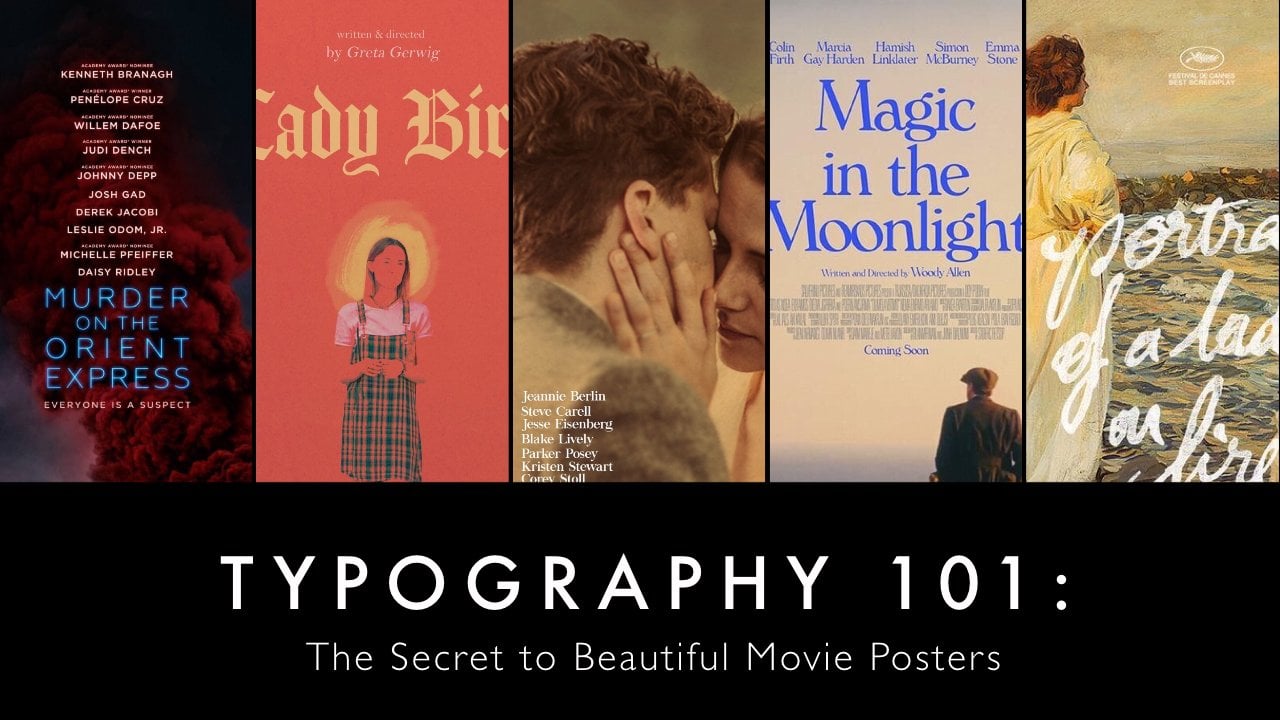
Tipografía 101: el secreto para hermosos carteles
¿Alguna vez te has visto fascinado por un póster de películas absolutamente hermoso? ¿Y te preguntas por qué es tan hermoso? Bueno, has venido al lugar correcto.
En última instancia, el secreto de los hermosos pósters de películas es la tipografía, el arte de usar texto. En este curso de tipografía 101, aprenderás qué hace que ese póster de películas sea tan hermoso y aprenderás cómo diseñar un póster de películas como ese.
1. Tipografía 101: tráiler de introducción: ¿ Alguna vez te has encontrado siendo hipnotizado por un póster de película absolutamente hermoso? Y te preguntas, ¿por qué es esto tan hermoso? ¿ Es la fuente que utilizan para un espaciado perfecto entre las letras son disposición proporcional de los textos o vía combinación de colores estáticos. En última instancia, para carteles de película secretos a bellos es la topografía. El arte de usar texto. En este curso tipo de grafeno 0101, aprenderás qué hace tan lamentable ese póster de película. Y aprenderás a diseñar un hermoso póster de película así. Epigrafía uno a uno, ya que no se requiere un software costoso de conocimientos básicos sobre diseño gráfico o donde estés principiante al diseño gráfico o simplemente tienes curiosidad, este curso es para ti. Entonces, ¿estás listo para desbloquear el secreto? 2. Typeface vs. Font y qué fuente debe usar en un diseño: Hola a todos. Bienvenido al tipo de grafeno 0101 es secreto a hermosos carteles de película. En esta lección, aprenderemos cuál es la diferencia entre tipografía y fuente para el diseño. En primer lugar, tipografía versus engendrado. Una tipografía incluía múltiples fuentes de la misma familia, mientras que una fuente con un peso y un tipo de tamaño específicos dentro de esa familia. Por ejemplo, y este cartel, la tipografía es Futura. Pero más específicamente, la fuente es 22 largometraje en medio para los nombres de las actriz y 72 futuro o extra negrita para el título. Ahora, elegimos unas preguntas para cada diseñador ¿qué fuente usar en tu diseño? Hay dos factores a considerar a la hora de elegir una fuente. Practicidad y estética. Practicidad significa legibilidad. No importa lo bonito que sea cartelar, si la fuente es elegible, fan, es un mal diseño. Entonces, ¿cómo sabes si la fuente es práctica o no? Hágase esta pregunta, ¿ es esto fácil de leer? Preste atención al espaciado entre letras y espaciado entre palabras. Preste atención a la conducción de una brecha entre las líneas. Preste atención al color. Y si no hay suficiente contraste entre el color del texto y el fondo, será difícil de leer. Y por último, como regla general de oro, unas fuentes cursivas y caligráficas, más difíciles de leer y fuentes simples y mínimas. A continuación, hablemos de un set X. Un póster de película es hermoso o no porque la fuente en sí es hermosa. Pero donde sea porque la fuente simplemente va muy bien. El tema de la película. Por ejemplo, cuando vayas a Pinterest y busques una tipografía hermosa, se mostrarán muchas fuentes como esta. Echemos un vistazo más de cerca a esta tipografía. Fuente es Lovelace, fuentes zeta gris claro extra. El diseño del cisne es bastante increíble. Está compuesta por trazos gruesos y delgados. Esos detalles le dan a esta fuente una sensación muy elegante y elegante. No obstante, no tendría sentido que pongas una fuente como esta en carteles en movimiento. Así que asegúrate de elegir una fuente que se adapte bien al tema de la película, y no solo a cualquier tipo de letra hermosa. Tener una mejor comprensión de lo que he estado hablando. Echemos un vistazo a algún grado así como a algún mal diseño de póster de película. Estás mirando el cartel de la película Lady Macbeth, estrenada en 2016. Este es un ejemplo de práctico pero completamente carente de póster de película estética. Un elegido formado, es muy legible. Específicamente, se trata de textos unitarios sonda negrita. El espaciado es razonable. No está demasiado apretado ni demasiado lejos. Es cómodo de leer. color amarillo del texto realmente sobresalen. No obstante, no veo ninguna conexión entre el texto y el fondo. Buscando desde un alfabeto, eso significa que el personaje está usando. Supongo que este escenario cinematográfico está en el siglo XIX. Es la fuente simplemente no recuerda a la gente del siglo XIX en absoluto. Además, la combinación de colores de azul y amarillo es una especie de no relacionado. En general, creo que no lo es. Ok diseño, pero el diseñador podría haber hecho un trabajo mucho mejor. Aquí hay una mejor alternativa. Creo que esta paleta de colores funciona mucho mejor que la combinación amarilla y azul. Puede que no te des cuenta, pero en realidad usaron una fuente diferente en este diseño. Sigue siendo una fuente mínima como la última vez. Pero esta vez da una limpieza misteriosa de suspense. Creo que eso se debe a la cita citada en la mitad superior del cartel. Esos códigos 12. Esta película es en realidad sobre asesinato. Crt tiene sentido usar una fuente que se usa comúnmente en muchas otras películas de resolución de misterios, como Murder on the Orient Express, death on the Nile, The Girl on the Train. Un diseño que comete los mismos errores es el póster de película para la serie y con una e en Netflix. De nuevo, eso es definitivamente legible. No hay mucho trabajo que hacer realmente. Es sólo una palabra y una línea corta. Elegido Font me recuerda están en Microsoft Word. Es un deseo tan anticuado para titulares hoy en día. Y definitivamente no es adecuado para una película basada en una novela de llegada de la edad sobre el objetivo del orfanato a finales del siglo XIX. La combinación amarilla y azul está realmente fuera de la nada. Aquí hay una mejor alternativa. Me gusta mucho la paleta azul pastel morado en este póster de película. También una fuente utilizada para la línea, Bienvenido de nuevo a Green Gables, se adapta muy bien al tema de la película. Veamos un último ejemplo. Aquí está el cartel de la película el gran dorado, estrenada en 2017. Esta vez, este póster de película es extremadamente ascético, pero tristemente, ilegible. Las fuentes aquí realmente expresan la FIM de la película, que es femenina y romántica, pero también oscura y algo prohibida. También son hermosos los colores. Rosa suave apenas saca elemento femenino de la película. Pero es cierto que es difícil de leer. En primer lugar, no entiendo por qué todos los textos son verticales en lugar de horizontales. En segundo lugar, la fuente utilizada título permitido es una tipografía de guión formal caracterizada por trazos de Francia cursivos y conectados que sugiere elegante, aunque definitivamente se adapta muy bien al tema de la película. Definitivamente no es algo que la gente va a entender en un corto lapso de atención. Ahora, mira este diseño. Han mejorado girando todo a horizontal, pero aún así mantienen la misma fuente para el título sobre la fuente, queremos algo que mantenga la vibra de la tipografía de script formal, pero también necesitamos algo que sea más legible. Este diseño alternativo solo consigue lo mejor de ambos mundos. Honestamente, creo que este es un diseño muy inteligente. Solían escribir la fuente formal para la primera letra y una tipografía serif para la detención. Con todo, la clave de los hermosos carteles de películas realmente es equilibrar el elemento de practicidad y el elemento estético. Eso es todo por este video de la lección. Espero que hayan tenido una mejor comprensión de la tipografía. Gracias por ver, y los veré en el siguiente video de la lección. 3. Categorías de tipos (Serif y San Serif): Hola a todos. Bienvenido al tipo de grafeno 0101, el secreto para construir carteles de película entera. En esta lección, pasaremos por alguna terminología topográfica en diferentes categorías de tipos de letra. En primer lugar, echemos un vistazo a alguna terminología topográfica básica. estrés se refiere a la línea invisible que disecciona la hendidura de arriba a abajo en nosotros punto de meta. Se puede ver para subrayar lo más obvio y la letra O aquí son a 0 de dos tipos de letra diferentes. Dibujas una línea de arriba a abajo en su punto espinoso. A la derecha, la línea es diagonal, por lo que la llamamos tensión diagonal. En tanto que la izquierda, la línea es vertical, por lo que la llamamos estrés vertical. Siguiente sección es cualquier tipo de trazo o línea o el núcleo adjunto a este último. Por lo general, existen dos tipos de protección. Serif y terminal. Servir se refiere a la línea corta o trazo en extremos abiertos de letras. Terminal es el final de un trazo que no es un serif. Y por último, el soporte es curvado o visto conexión de línea entre el tallo y un serif de algunos pensamientos. Ahora, pasaremos por dos categorías principales de tipografía, serif y sans serif. En primer lugar, serif. tipografía Serif incluye una ligera protección rematando los trazos de sus formas de letra. Estas categorías se pueden dividir aún más en cinco subcategorías. Serie de estilo antiguo, serifs transicionales, serifs modernos, serifs de losas, y arabes clearfix, quienes principalmente examinan elementos libres para distinguir estas cinco subcategorías. El estrés es la diagonal del mercado vertical. ¿ Tiene proyecto? Y el nivel de contraste entre trazos gruesos y delgados? De lo contrario, mencionaré cualquier otra diferencia notable. Serifs de estilo propio caracterizados por una tensión diagonal, un contraste mínimo entre trazo grueso y delgado. serifas están en una forma y casi siempre son corchete. serifs de cabeza suelen estar en ángulo. Un ejemplo de una tipografía serif de estilo antiguo es Garamond. Continuando, el serif transicional suele tener trazos verticales, estrés vertical, y hay un contraste más pronunciado entre trazos gruesos y delgados en comparación con las serifs de estilo antiguo. serifs son paquetes y las serifs de cabeza son clink. Un famoso ejemplo de serifs transicionales es Baskerville. A continuación, las serifs modernas se caracterizan por el dramático contraste entre trazos gruesos y delgados. Por ejemplo, de trazos curvos es vertical. serifas son inherentes, en forma de línea y práctica. Firma numérica de las serifs modernas, Chartres es los terminales en forma de bola. Dos tipografía serif moderna de uso común o viudo y Bodoni continúan. series de losas típicamente incluyen serifs muy pesados con muy bajo o sin agrietamiento. No hay contraste y el peso del trazo. Un ejemplo bien conocido sería Rockwell. Por último, las Teorías de Conflictos se distinguen por el serif de forma triangular diseñado o extremos de trazo cónico, contraste mínimo y peso de trazo. Y el eje de los trazos curvos tienden a ser verticales. Un ejemplo de tipografía clásica serif es arbitrario. Ahora veamos algunos ejemplos para ver dónde sería apropiado usar una tipografía serif. Aquí te dejamos tres hermosos carteles de película o usa tipografías serif. De izquierda a derecha. Nos dieron media sociedad donde listas y 2016 para nuestra multitud de formateo, estrenada en 2015 y perdida en traducción, todo el 1003 Oscar ganando al mejor guión original. Entonces, ¿cuál es la sensación general pero la tipografía serif traída a estos carteles gratuitos? Da a los espectadores el clásico dedica sofisticado, un sentimiento elegante. Entonces, en general, si tu diseño tiene un estilo clásico y tradicional y serio, sería genial usar una tipografía serif. Continuando, sans serif. tipografía Sans serif no incluye ninguna proyección al final de los trazos de la forma de letra. Esto se puede dividir aún más en cuatro subcategorías, grotescas y neocortex sans serif a sensor métrico de un humanista sans serif. En primer lugar, para tarea y nuevo grotesco sans serif, hay un mínimo de contraste y peso de trazo y una calidad de rebanada cuadrada. Demasiadas curvas. Después de ejemplos famosos están Arial y Universo. Siguiente es geométrico sans serif. Estas tipográficas se caracterizan por su forma de suelo de la letra o.Las formas de carácter están compuestas formas geométricas simples y no hay contraste entre trazos. Estas piezas son muy comúnmente utilizadas en póster de cine, notablemente futuro. Y por último, san-serif humanista. El único rasgo que distingue sensorial humanista supervisión del mismo es el aparente contraste y el peso del trazo. Algunos ejemplos son un Gill Sans y Fergana. Echemos un vistazo a algunos carteles de películas increíbles, pero use la tipografía sans serif para ver los sentimientos. Pero sans serifs podría dar a un diseño. Aquí te dejamos parásito, los Oscar 2020 ganadores a Mejor Película del Año. El langosta lanzado en 2015. Y un 55 gratis, que nunca sabremos. Cuándo se dará a conocer. tipografía Sans serif típicamente aporta un cinco muy mínimo, limpio, moderno, innovador al diseño. Por lo tanto, en general, siempre que estés haciendo un póster de película de ciencia ficción, una película de resolución de misterios, o básicamente cualquier tipo de letra serif de género asignado siempre será una gran opción. Eso es todo para la lección de hoy. Muchas gracias por ver. Te veré en el siguiente video. 4. Categorías de tipografía (cont.): Hola a todos. Bienvenido al tipo de grafeno 101 es secreto a hermosos carteles de película. En la lección de hoy, seguiremos introduciendo en las tres categorías superiores de tipos de letra. Primera parte, tipografías de script. tipografías de script se caracterizan por trazos fluidos de escritura a mano, que van desde formal hasta casual. Por lo general se utilizan con fines decorativos. Existen tres subcategorías de guión. Tipografías. Scripts formales, guiones casuales o caligráficos, y guiones de letras en placa, cada uno aporta una sensación diferente al diseño. En primer lugar, los guiones formales para más tifus de matorral imitan la escritura formal del siglo XVII. Por lo general tienen trazos de conexión, bucles fluidos y florece por guiones de mano como caracol, mano redonda son dos ejemplos de guiones formales. Encontrarás que el tifus de matorral formal es de uso común. Invitaciones, anuncios, y carta de iniciales decorativas. Ayudan a establecer un tono elegante, sofisticado, y lo más importante, femenino. Realmente se usan en carteles de películas. Dos ejemplos que encontré son el campo grande y Billy Elliot. Se les mata es la película escrita y dirigida por Sofía Coppola, estrenada en 2017. Hemos repasado este póster de película en menos de uno. El tipo de guión formal en algún color rosa, perfectamente expresado con algunos de la película, que es femenina, romántica, pero también oscura y misteriosa. En tanto, veamos el cartel de la película de Billy Elliot. Aquí. El diseño también utilizó una fuente similar en color rosa suave. Creo que es un diseño brillante porque nota cómo el chico no se queda completamente detrás o frente al texto. A diferencia de las chicas rodean a Kim, que están todas completamente detrás del texto. Este espectáculo tiene un niño lucha por encajar en este mundo del ballet y el arte feminista definitivo. Y esa es toda la historia de la película. Algunos recordatorios, bueno, solo usan tipografías de script formales para titulares o frases cortas. Desde párrafo largo de texto, guión establecido y formal o no legible, también, nunca los escaneó en todos los mayúsculas que no están diseñados para usar así. A continuación, guiones casuales o caligráficos. Los guiones casuales o caligráficos imitan nuestra escritura cotidiana casual, pero el lápiz o el pincel usan guiones casuales para llevar un formato amistoso o crecimiento personal a tu diseño. Aquí te presentamos algunos usos icónicos de guiones casuales y carteles de películas. En primer lugar, llámame por Tu Nombre, póster de película. El uso de una fuente de escritura a mano muy suelta y casual, combinando con una hermosa paleta de colores da como resultado un diseño absolutamente notable. sólo mirar el cartel, los espectadores ya están caminando hasta el verano de Italia, Listos para presenciar una historia de amor del SAT. De igual manera, por la culpa y nuestras estrellas, nada podría salir mal si utilizas la fuente de guión correcta con la paleta de colores correcta. El tema en color negro, blanco, azul es consistente con el diseño de la portada del libro, haciendo que la película sea reconocible para este libro Phantom. El crayón textura de esta tipografía simplemente crea un ambiente de internet pero lúdico de la historia de amor adolescente. En conjunto, las hidrolasas de guión casual típicamente funcionan bien con historias de amor porque trae unos sentimientos tan personales e íntimos al diseño. Por último, una letra guiones. También se les llama guiones góticos o ingleses antiguos. Son fácilmente reconocidos por los trazos traumáticos delgados y gruesos tan pequeños como el intrincado diseño de la forma de letra. Pero los guiones de letras se utilizan con frecuencia en certificados, diplomados, títulos, y sobre todo periódicos significan placas. Apenas se usan en el póster de la película. Pero Lady Bird es una excepción. las letras se escriben a sí mismos, como algo muy formal y serio. En tanto, el cartel es básicamente un retrato de una joven mujer de pelo teñido rosa. Es una salvaje, única. Y todo esto no está destinado a ser para más serio en absoluto. Creo que ese es un contraste realmente genial. Y si realmente miras de cerca el cartel, verás que está lleno de contraste. Por lo que para ardilla es usar un viejo estilo menos confianza con un collar de perlas o tener su cabello teñido de rosa y cortado. El fondo desenfoque es en realidad la preparatoria católica, pero ¿pasa por ella, pero probablemente sea cualquier cosa menos conservadora y tradicional crecer. Ya ves, está lleno de culturas y resulta ser un póster de película absolutamente hermoso. Pasemos a la parte 2, caras tipo monospacadas. Las caras de tipo monospaced se caracterizan por una cantidad igual de espacio horizontal para cada personaje toma. Se utilizan codificando programas informáticos o escribiendo con una máquina de escribir. Corea es un famoso ejemplo de una fuente monospace. Será genial usar una fuente monospace en un póster de película. Si la máquina de escribir consiguió una conexión interesante o importante con la historia. ¿ Puede alguna vez perdonarme, lanzado en 2018 es un gran ejemplo. Y por último, tipografías de exhibición libre de parte. tipografías de exhibición son dos oficinas que están diseñadas específicamente para títulos y titulares. Se pueden crear tipógrafos con estas superficies para crear un título único de los carteles de la película. Muchas series de franquicias y películas tienen uno de los tipos de letra actuales para sus títulos, como la serie Harry Potter, la Serie Adventure, Captain America, Iron Man, o básicamente todas las series de películas de superhéroes. Y eso es todo para la lección de hoy. Muchas gracias por ver. 5. Jerarquía tipográfica: Hola a todos. Bienvenido de nuevo a tipográfico. Quieres aprender el secreto a hermosos carteles de película. En esta lección, aprenderás sobre la jerarquía tipográfica, parte 1. ¿ Cuál es la jerarquía tipográfica? Una jerarquía tipográfica es un sistema organizador para establecer orden en un cuerpo de textos y ayuda al espectador a encontrar información específica, pero editando diferentes tipos de información en diferentes estilos. Echemos un vistazo a algunos ejemplos. Esta es alguna información sobre la próxima exposición que el museo está promoviendo. Si no te dije eso, quizá ni siquiera lo sepas. ¿ De qué se trata esto? Porque aquí no hay jerarquía tipográfica. Toda la información se edita en el mismo estilo, misma fuente, mismo tamaño, mismo color, mismo todo. Y esto es lo que obtuviste cuando creas una jerarquía tipográfica. Tan solo un par de cambios en tamaño y peso. Ahora los espectadores pueden encontrar la información que necesitan. Ahora para carteles de películas, esto es lo que sucede cuando no se tiene una jerarquía tipográfica y el diseño a mal transmite cualquier información, y es difícil incluso decir cuál es el nombre de la película. Una vez que lo arreglas creando una jerarquía muy simple y básica. Cosas en marzo más claras. Pasando a cómo crear una jerarquía tipográfica. Se trata de un proceso de tres pasos, incluido el paso uno, Identificar la información que necesita incluir bajo diseño. Para póster de película, ese suele ser el título de la película, nombre del actor, el nombre del director, y una línea de gancho para llevar a la gente al teatro. Paso para organizar la información en el orden de lo más a lo menos importante. Esto depende de la situación, pero generalmente el título de la película LP, y luego los nombres de los actores, el nombre de los directores, y Hotline pueden estar todos en el mismo nivel. O si quieres resaltar el nombre de un actor mirando la película o del director de la película. Después mueve esa información a un nivel. Por último, el paso 3 es averiguar cómo hacer que esa jerarquía sea reconocible para los espectadores. Aquí hay seis maneras de hacer eso. Número uno, tamaño, su símbolo. grande significa más importante, y más pequeño significa más número importante para esperar. Hacer una tipografía más audaz o más delgada es una opción para ti. Número 3, color. Dado que todos los textos son de color invisibles, usa tonos más claros de ese color para obtener información menos prominente y tonos más oscuros para los importantes. O puede usar el color que contrasta claramente el fondo para el título, y menos contraste en colores para la información. Número 4, caso usando caracteres en mayúscula para el título diferenciado de otra información. Número 5, posición y alineación, donde se pone la información sobre el diseño y la alineación de los textos puede mostrar el nivel de importancia de esa información. Por lo general, la información más importante se colocará en el centro del diseño y el centro alineado. Por último, el número 6, una combinación de todo lo anterior. A veces, los diseñadores combinan dos o más de las opciones para diferenciar eficazmente diferentes niveles de la jerarquía. Una edición especial es divertida. uso de diferentes fuentes para diferentes tipos de información puede ayudar a construir jerarquía. Pero esto por sí solo no será efectivo. Por lo que lo mejor es emparejarlo con algunos métodos. Y eso son todos los pasos generales. Consulta la siguiente lección para tutorial detallado paso a paso de cómo construir una jerarquía tipográfica básica. 6. Cómo crear tu propio afiche de películas: Hola a todos, Bienvenidos de nuevo al objetivo graficando 101, el secreto a hermosos carteles de película. En esta lección, te mostraré cómo construir tu propio póster de película. hoy, vamos a rehacer un diminutivo Kruskal durante 500 días de verano. Seguiremos los pasos generales de la última lección. En primer lugar, enumerar la información que necesita incluir en el diseño. Segundo, los dispuso en un orden de lo más a lo menos importante. A continuación, debes elegir una imagen de fondo. Aquí, tienes muchas opciones. Puedes elegir una escena hermosa de la película, o puedes usar fotos que se rompan específicamente para el póster de la película. O algunos diseñadores pueden construirlo completamente desde cero. Podrás encontrar y descargar estas fotos desde un sitio web llamado movie mania.com llamado proporcionar papel tapiz de películas de alta calidad, insípido, directo, simplemente perfecto para nosotros. Por lo que entras al sitio web, busca tu película favorita, como la imagen que prefieras, luego haz clic en el botón azul para descargarla. Ahora, iremos a Canvas para empezar a diseñar. Puedes usar la versión web o la versión de la app. Actualmente estoy usando el lienzo de la app en mi iPad. Selecciona, Crea un diseño y elige Póster para subir imágenes. Seleccione el icono Subir en la barra de herramientas de la izquierda y, a continuación, seleccione Subir medios. Subiré la imagen de mi fototeca. Basta con hacer click en la imagen para añadirla al póster, tira de la esquina para que Emerick, ella llenara toda la página. Volvamos al paso tres. Antes de continuar. Recuerda, hay seis formas de crear una jerarquía tipográfica. Tamaño, peso, color, Ks, alineación, y posición, y forma. Los diseñadores suelen usar una combinación de dos o más de estos seis métodos. Los principiantes deben comenzar con una combinación de dos. Y a medida que te vuelvas más experimentado, intenta combinar todos los métodos. La combinación más básica son los signos y alineación y posición. Es la forma más fácil de conseguir una jerarquía decente. Entonces probemos eso. Volver a Canva para agregar textos, detectos leves o icono en la barra de herramientas de la izquierda. Seleccionar, Agregar un subtítulo escrito en el nombre de la película. Y todas las pestañas. Repite los pasos para agregar en nombre de los actores, el director, y la línea de gancho, muchas veces en todas las tapas del mismo tamaño que nosotros y caemos. Ahora, antes de aplicar los métodos, Cambiemos la fuente a amar la ley. Ahora. Primero lo primero, tamaño, aumentó tamaño del título a 95. A continuación, disminuir el tamaño del nombre del actor, 250. Aquí, estás tratando de usar el tamaño del texto para mostrar a los lectores lo que es más importante y lo que es menos importante. Por lo tanto, la diferencia de tamaño se determinará por la distancia entre los niveles de la jerarquía por nombre de los actores es significativamente menos importante que el título de la película. Por lo que el tamaño de los nombres de los actores también debe ser significativamente menor que el tamaño del título de la película. No obstante, el director y la línea de ayuda no son tan significativamente menos importantes, pero los nombres de los actores aquí porque sólo voy a reducir el tamaño 240. A continuación, aplique nuestro segundo método, alineación y posición. Para mantenerlo sencillo, mantén todo alineado al centro. Ahora, puedes mover el texto y arreglarlos. Prueba el arreglo clásico poniendo el nombre del actor en el borde superior. Pon el título de la película abajo malo en el centro del cartel. Ahora, puesto dirigido por Merck, que tienen justo debajo del título de la película. Entonces ahora lo estás mirando. La parte superior del cartel ya está bastante abarrotada, por lo que moveremos la línea de gancho hacia abajo hasta la parte inferior y también la pondremos en el centro así. Y ya terminaste. Prueba esto por tu cuenta. Después de esto, puedes probar una combinación de tres o cuatro métodos. Sigue practicando y te pondrás mejor. Y ese es el final del curso. Muchísimas gracias por ver.